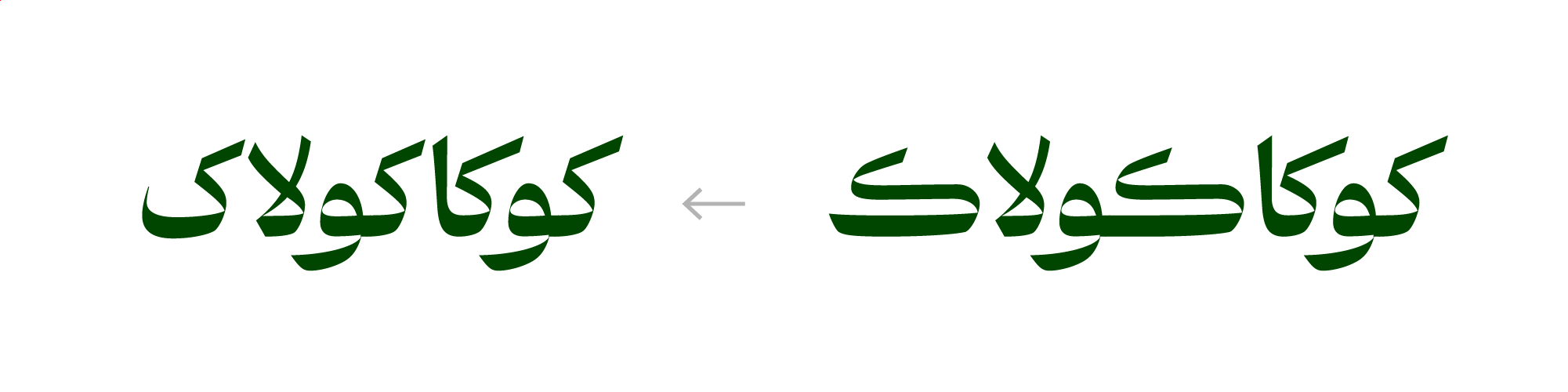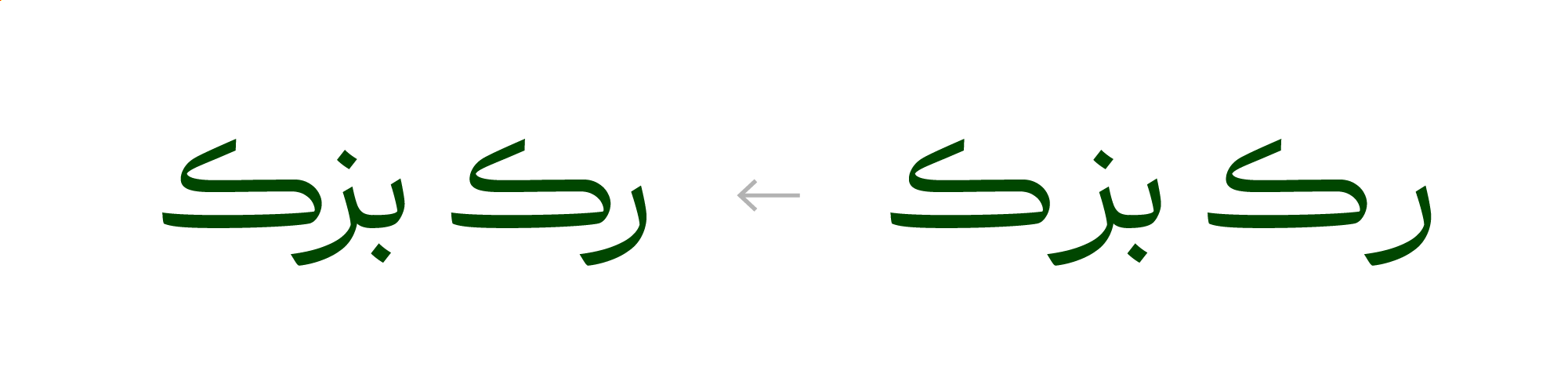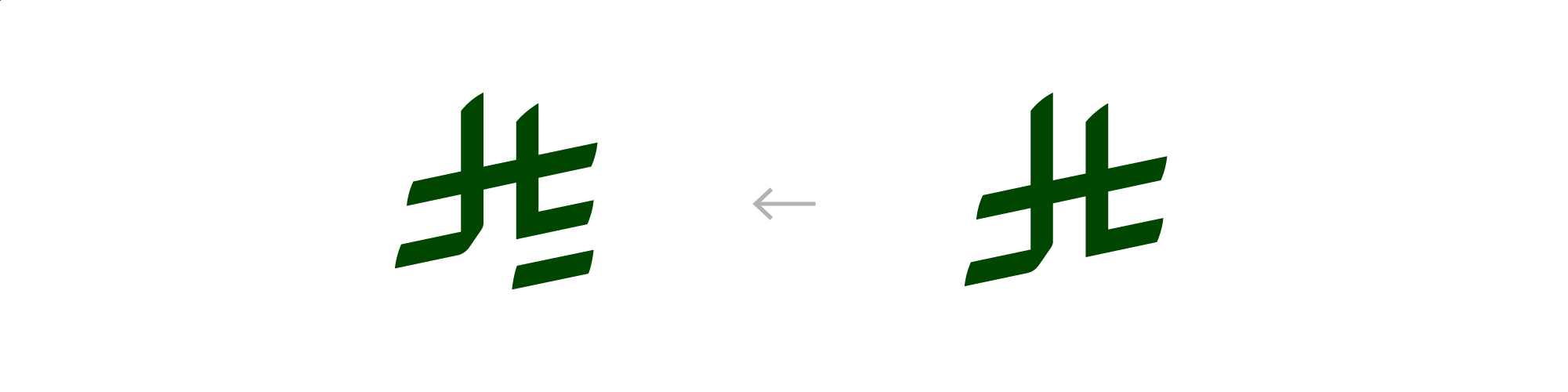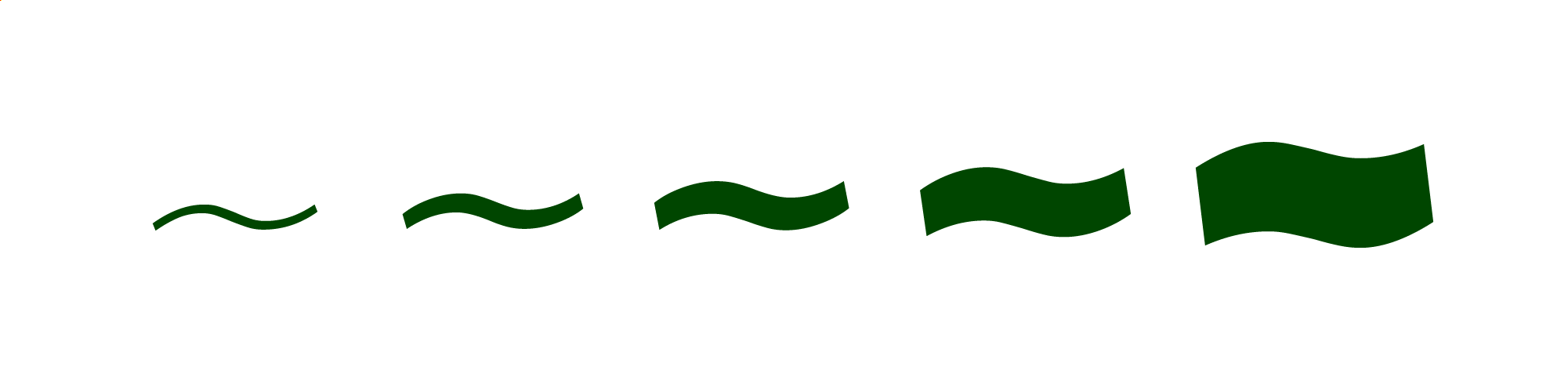
در نسخهی ۲٫۱ فونت ابَر چه تغییراتی میبینیم؟
1. «ک» سرکش کوتاه بازگردانده شد. در ترکیباتی که سرکش با حرف قبلی برخورد میکند، سرکش «ک» کوتاه میشود. در صورتی که میخواهید «ک» کشیده جایگزین شود، Stylistic Sets 14 را فعال کنید.
2. مشکل فاصلهی «ک» کشیده با بعضی حروف برطرف شد.
3.نقطهی نماد «ریال عربستان» جامانده بود! بازگردانده شد.
4. نماد Tilde “~” به فونت اضافه شد.